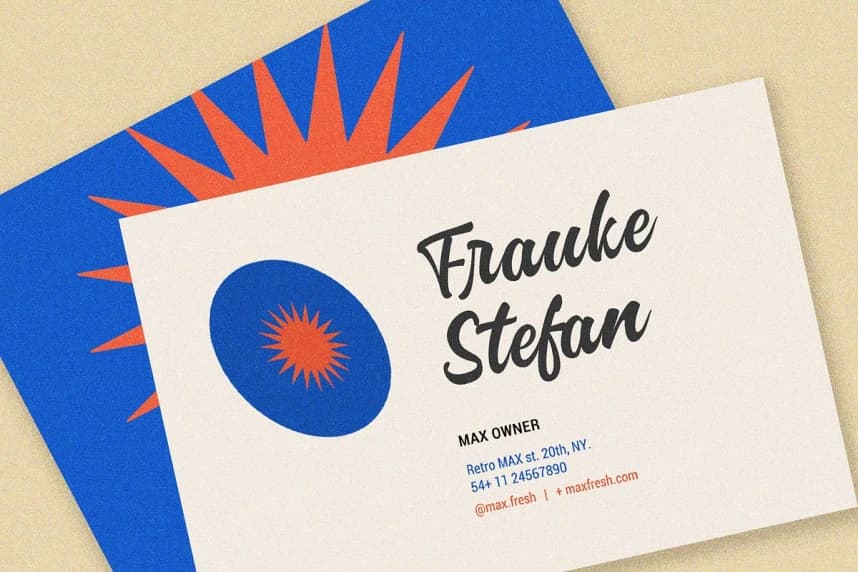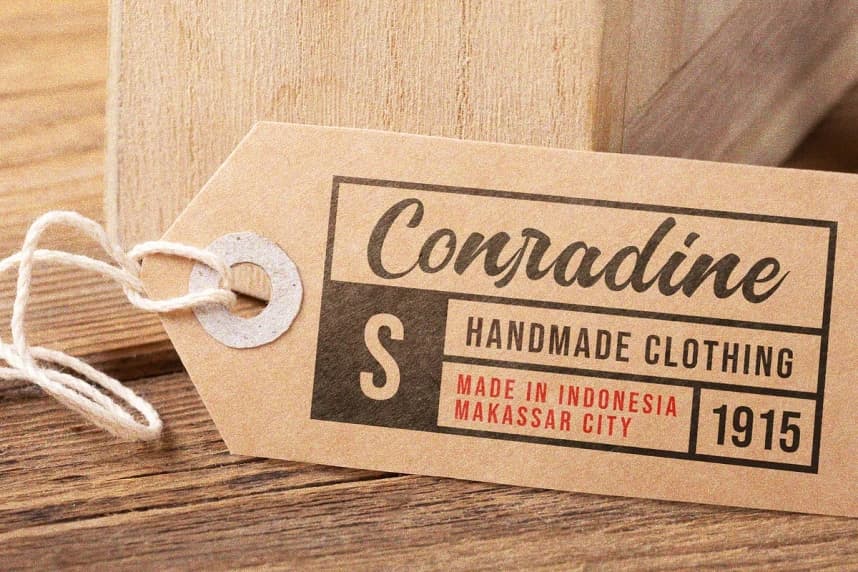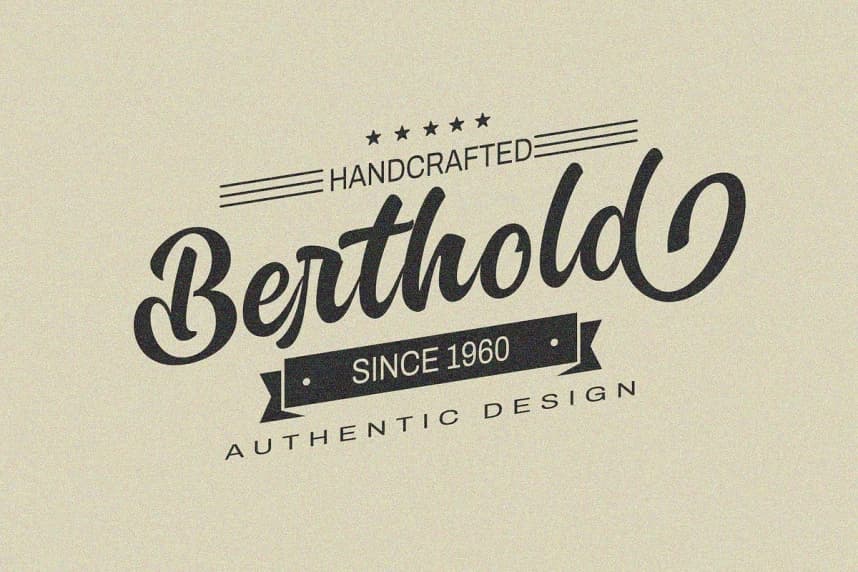
Volks Tiyatro Yazı Tipi
Volks Theatre Font şık bir yazı tipidir. Hem modern hem de retro bir görünümü vardır. Alternatifler ve ligatürlerle birlikte gelir; çarpıcı logolar, alıntılar, gönderiler ve blog yazıları oluşturmaya yardımcı olur. Markalaşma projeleri, dergi görselleri, düğün davetiyeleri ve çok daha fazlasını içer
Volks Theatre Font şık bir yazı tipidir. Modern ve retro bir görünümü vardır. Alternatifler ve ligatürlerle birlikte gelir; çarpıcı logolar, alıntılar, gönderiler ve blog yazıları oluşturmaya yardımcı olur. Markalaşma projeleri, dergi görselleri, düğün davetiyeleri ve çok daha fazlası.
Volks Theatre